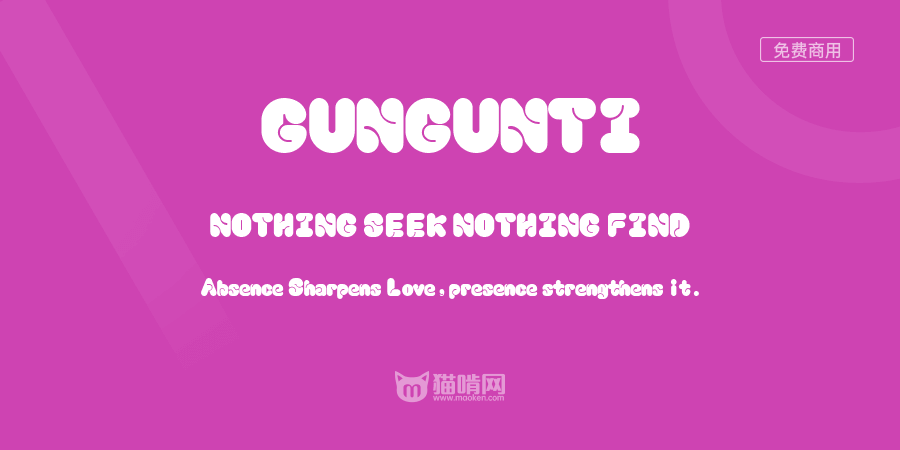
GUNGUNTI
字体作者:黑洞品牌研究所 (中国大陆) 字体字重:1个
小黑滚滚体 / 英文字库设计
设计团队丨GoodnitDog studio 观念狗
完成日期丨2024年3月
字体设计丨小黑
动效设计丨入墨 / 北也
字体简介
《小黑滚滚体》,秉承自由的理念,浑厚可爱,运用圆滚动后的痕迹形成正负形的形式,根据书写逻辑融合几何图形运动去表达,用在标题、logo文字中效果极佳。